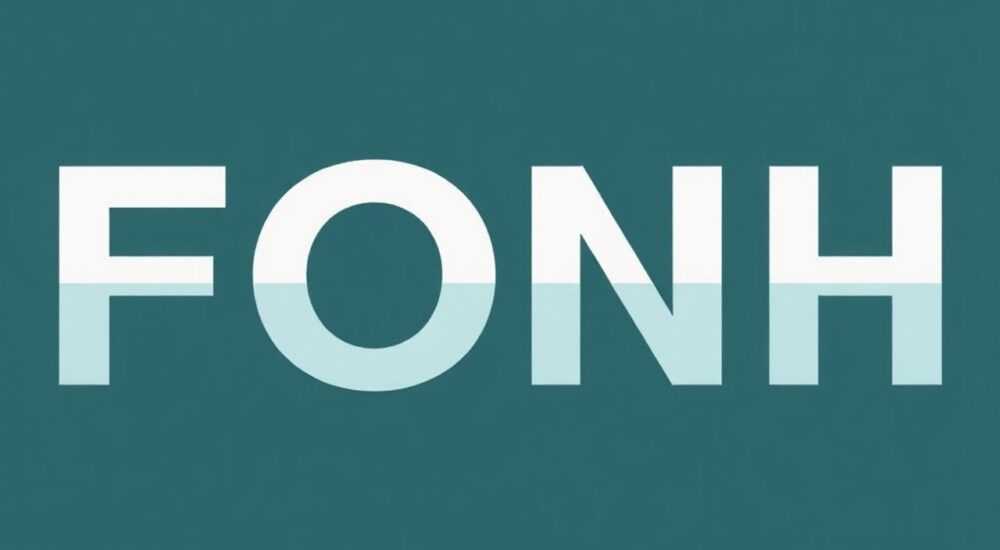
Как создать шрифт в фотошопе
Создание шрифта в Photoshop — задача, которую многие пользователи путают с дизайном типографики с нуля. На самом деле, Adobe Photoshop не предназначен для разработки полноценных кастомных шрифтов (в формате .ttf или .otf), но позволяет создавать уникальные текстовые эффекты, стилизованный текст и визуальные элементы, которые можно использовать как «шрифт» в рамках одного проекта. Основная цель — превратить обычный текст в художественно оформленный элемент с помощью инструментов растровой графики.
Создание собственного шрифта — это не просто мода, а необходимость для брендов, дизайнеров и креаторов, которым важно выделиться. Однако важно понимать: если вы хотите получить файл, который можно установить в систему и использовать в Word или InDesign, Photoshop не подойдёт. Но если ваша цель — сделать уникальную надпись для логотипа, обложки или баннера, то Photoshop предоставляет мощные инструменты для визуальной трансформации текста. В этой статье мы подробно разберём, как максимально эффективно использовать возможности Photoshop, чтобы достичь эффекта «своего шрифта», какие шаги предпринять, какие ошибки избегать и как экспортировать результат.
Что значит «создать шрифт» в контексте Photoshop?
Когда пользователи спрашивают, как создать шрифт в Photoshop, они часто имеют в виду не разработку полноценного векторного шрифта, а создание уникального стилизованного текста. В отличие от программ вроде FontForge, Glyphs или Adobe Illustrator, Photoshop работает с растровыми изображениями. Это означает, что любой текст, даже при создании через векторный инструмент «Текст», при масштабировании может потерять чёткость, если его конвертировать в пиксельный слой.
Тем не менее, Photoshop идеально подходит для создания так называемых «визуальных шрифтов» — текстовых композиций, где буквы обрабатываются с помощью эффектов: теней, градиентов, текстур, объёмов и других визуальных приёмов. Такой подход часто используется в брендинге, рекламе и цифровом искусстве.
Даже если вы не можете экспортировать свой дизайн как .ttf-файл, вы можете сохранить стиль текста как «Стиль слоя» и применять его к другим надписям. Это особенно полезно при работе с корпоративными шаблонами, где требуется единый визуальный язык.
Пошаговое руководство: как стилизовать текст под уникальный шрифт
Создание уникального текстового стиля в Photoshop — это процесс, который можно разбить на несколько этапов. Даже начинающий пользователь сможет повторить эти шаги и получить профессиональный результат.
- Выберите базовый шрифт. Начните с установки или выбора подходящего шрифта из библиотеки Photoshop. Например, для минималистичного логотипа подойдёт Sans-serif (Helvetica, Futura), для винтажного — шрифт с засечками (Times New Roman, Georgia) или рукописный стиль.
- Напишите текст с помощью инструмента «Текст» (T). Убедитесь, что вы работаете с векторным текстовым слоем. Не растрируйте его на этом этапе.
- Настройте размер, межбуквенный интервал и выравнивание. Используйте панель «Характер» (Window → Character), чтобы точно контролировать расстояние между буквами (кернинг) и строками (интерлиньяж).
- Примените эффекты наложения. Дважды щёлкните по слою с текстом, чтобы открыть «Стили слоя». Здесь можно добавить тень, контур, градиент, наложение текстуры и другие эффекты.
- Добавьте детали вручную. Создайте новый слой под текстом и вручную дорисуйте элементы: трещины, блики, узоры. Используйте кисти с текстурой для имитации старения или металлического блеска.
- Сгруппируйте слои и сохраните стиль. Выделите все связанные слои, кликните правой кнопкой и выберите «Создать группу». Также сохраните стиль слоя, нажав на значок дискеты в окне «Стили слоя».
- Экспортируйте результат. Сохраните файл в формате PNG с прозрачным фоном или PSD для дальнейшего редактирования.
Как сохранить и переиспользовать стиль
Photoshop позволяет сохранять стили слоёв как пресеты. После настройки всех эффектов:
- Откройте палитру «Стили» (Window → Styles).
- Нажмите на значок «Новый стиль».
- Введите имя (например, «Металлический логотип»).
- Сохранённый стиль можно применять к любому другому текстовому слою одним кликом.
Инструменты и эффекты для создания шрифтовых стилей
Photoshop предлагает широкий набор инструментов для визуального преобразования текста. Вот основные из них:
- Слоевые стили (Layer Styles) — ключевой инструмент. Позволяет добавлять тени, свечения, градиенты, контуры и наложения без изменения исходного текста.
- Маски слоёв — помогают частично скрывать текст, например, чтобы создать эффект растворения или наложения на текстуру.
- Кисти (Brush Tool) — используются для ручной доработки букв, добавления трещин, потёртостей, бликов.